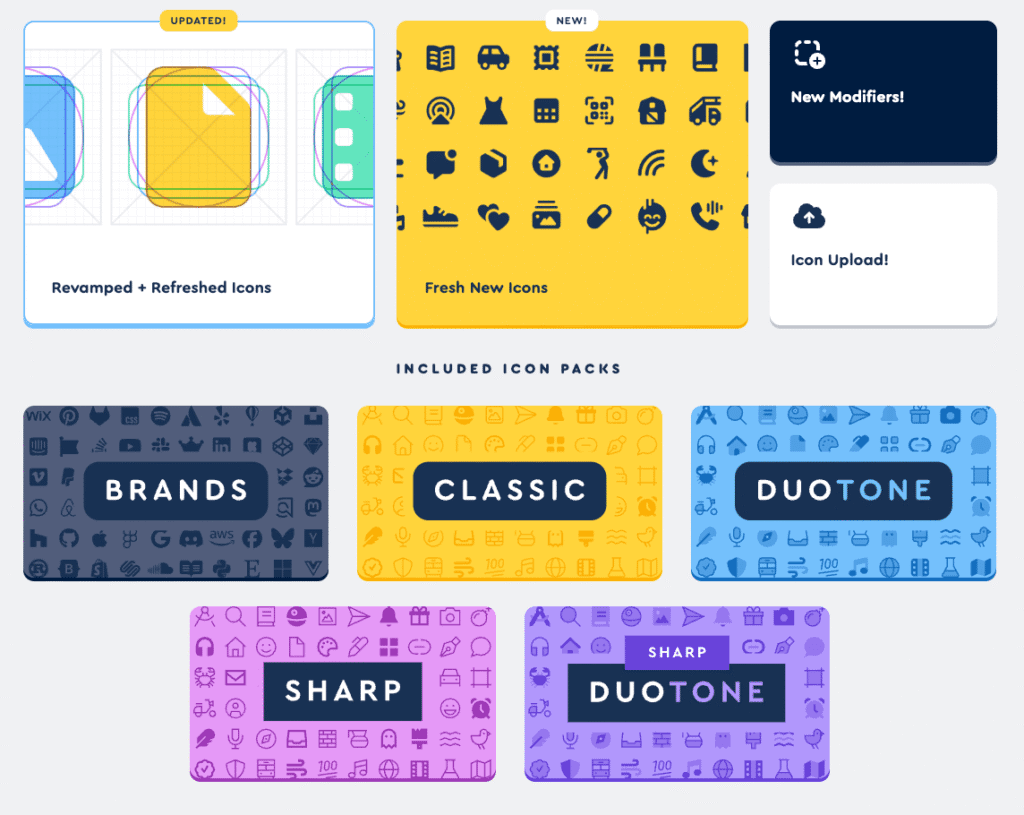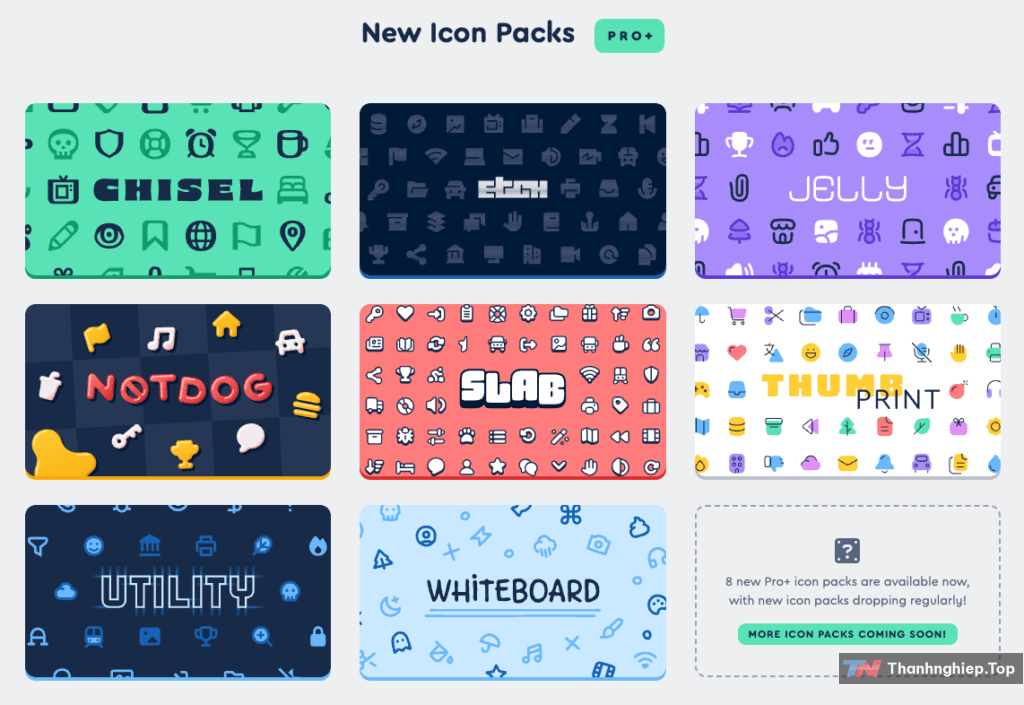
Chào các bạn yêu thích thiết kế web và icon! Hôm nay mình siêu hào hứng khi được chia sẻ với các bạn về phiên bản mới nhất: Font Awesome 7 Pro free download. Nếu bạn đang tìm cách làm cho website của mình trở nên sinh động hơn, thì đây chính là “bữa tiệc” icon mà bạn không thể bỏ lỡ. Font Awesome đã chính thức ra mắt phiên bản 7 vào tháng 6 năm 2025, và nó mang đến một loạt cập nhật “ngon lành” khiến mình phải wow liên tục. Hãy cùng mình khám phá nhé!
Tại Sao Font Awesome 7 Lại “Hot” Đến Thế?
Trước tiên, cho những bạn mới biết đến Font Awesome, đây là bộ thư viện icon miễn phí và trả phí siêu phổ biến, được sử dụng trên hơn 200 triệu website trên toàn thế giới.
Phiên bản 7 không chỉ là một bản cập nhật nhỏ, mà là một cuộc “lột xác” toàn diện. Đội ngũ Font Awesome đã tinh chỉnh lại toàn bộ các icon hiện có, làm chúng sắc nét hơn, hiện đại hơn, và thêm vào đó là hàng tá tính năng mới để giúp bạn dễ dàng tùy chỉnh theo ý thích. Mình thấy phiên bản này giống như một bữa ăn đầy đủ dinh dưỡng: có món chính, món phụ, và cả đồ tráng miệng!
Tính Năng Mới Nổi Bật Của Font Awesome 7 Pro
Hãy nói về những “món ngon” mới nhé, mình sẽ liệt kê để dễ theo dõi:
- Refresh Toàn Bộ Icon Packs Cốt Lõi: Các bộ icon quen thuộc như Classic, Duotone, Sharp, và Sharp Duotone đã được làm mới hoàn toàn. Chúng giờ đây mượt mà hơn, phù hợp với mọi phong cách thiết kế. Nếu bạn đang dùng phiên bản cũ, upgrade lên sẽ thấy sự khác biệt rõ rệt!
- Hơn 4500 Icon Mới Toanh: Đúng vậy, bạn không đọc nhầm đâu! Font Awesome 7 bổ sung hơn 4500 icon mới, từ các biểu tượng cơ bản đến những thứ chuyên biệt cho web projects. Dù bạn làm app, blog, hay e-commerce, chắc chắn sẽ tìm thấy icon phù hợp. Và trong bản phát hành đầu tiên, đã có hơn 300 icon tươi mới được thêm vào.
- Pro+ Icon Packs Siêu Độc Đáo: Đây là “đặc sản” chỉ có ở phiên bản 7! Các bộ icon như Jelly, Whiteboard, Chisel,… với phong cách vẽ tay, sketch, hoặc chạm khắc, mỗi bộ có khoảng 200 icon phổ biến. Chúng dành riêng cho người dùng Pro+, giúp dự án của bạn nổi bật với style riêng biệt.
- Icon Wizard Nâng Cấp: Giờ đây, bạn có thể tùy chỉnh icon với hơn 1 triệu lựa chọn! Thêm modifier, chỉnh sửa, upload icon riêng – tất cả đều dễ dàng hơn bao giờ hết. Mình thử rồi, cảm giác như đang chơi game thiết kế vậy!
Điểm Nổi Bật Làm Nên Sức Hút
Điều mình thích nhất ở Font Awesome 7 là sự thân thiện với người dùng. Không chỉ thêm icon, mà còn tập trung vào trải nghiệm: từ việc dễ dàng tích hợp vào code (với CSS, SVG, hoặc Kit) đến các style mới như hand-drawn hay sketch, giúp thiết kế của bạn trở nên sáng tạo hơn.
Bộ icon pack mới trong Font Awesome 7 Pro
FA Chisel – Bộ icon khắc nét vượt thời gian
FA Chisel là bộ icon mang phong cách mạnh mẽ, sắc sảo và đầy cá tính, gợi cảm giác như những tác phẩm điêu khắc được trau chuốt kỹ lưỡng. Đứng sau thiết kế này là Laura Bohill, một nhà thiết kế tài năng đã thổi hồn vào từng chi tiết.
Sự tương phản rõ rệt giữa nét dày và nét mảnh giúp Chisel dễ dàng nổi bật trong mọi giao diện, từ website, landing page cho đến ứng dụng. Nếu bạn đang tìm một bộ icon đủ “nặng đô” để truyền tải ý tưởng rõ ràng và dứt khoát, FA Chisel chính là lựa chọn đáng tin cậy.
FA Etch – Bộ icon được rèn để tạo ấn tượng mạnh
FA Etch ra đời từ một ý tưởng táo bạo: tạo nên toàn bộ hệ thống icon từ một tấm kim loại liền khối. Kết quả là những biểu tượng có góc cạnh sắc nét, kết hợp cùng các khoảng bo tròn được “cắt gọt” chính xác, mang lại hiệu ứng thị giác rất mạnh.
Bộ icon này đặc biệt phù hợp với các dự án cần phong cách bold, kỹ thuật và chính xác, như dashboard, sản phẩm công nghệ hoặc thương hiệu hiện đại. FA Etch không dành cho sự an toàn – nó sinh ra để gây ấn tượng.
FA Jelly – Bộ icon mềm mại nhưng không hề yếu
FA Jelly mang đến cảm giác mềm mại, tròn trịa và thân thiện ngay từ cái nhìn đầu tiên. Bộ icon này lấy cảm hứng từ superellipse của nhà toán học Gabriel Lamé – hình dạng thường được gọi là squircle, kết hợp hài hòa giữa hình vuông và hình tròn.
Nhờ thiết kế này, Jelly đạt được sự cân bằng lý tưởng giữa tính vui nhộn và khả năng ứng dụng linh hoạt. Đây là bộ icon rất phù hợp cho app, sản phẩm số hoặc giao diện cần cảm giác thân thiện, hiện đại mà vẫn chuyên nghiệp.
FA Notdog – Bộ icon vui nhộn, đầy cá tính
FA Notdog là một cách tiếp cận hoàn toàn khác với những bộ icon truyền thống. Không quá nghiêm túc, không rập khuôn, Notdog mang đến cảm giác vui vẻ và “dị” một cách có chủ đích.
Bộ icon này cực kỳ phù hợp cho các dự án sáng tạo, startup, sản phẩm trẻ trung hoặc bất kỳ thiết kế nào cần thêm một chút hài hước và cá tính riêng. Không phải hotdog, cũng chẳng cần bánh mì – FA Notdog đơn giản là rất vui.
font awesome 7.1.0 Released September 30th, 2025:
- Bộ icon Pro+ Utility: Gồm 200 icon phổ biến nhất cho thiết kế (Utility, Utility Duo, Utility Fill).
- Thêm icon: Tor-browser, kettlebell, aeropress, chemex, v.v.
- Đã sửa lỗi hiển thị của các icon certificate, screen-users, school-unlock.
- caret icons được trả về kích thước nhỏ V6, thêm icon caret-large mới.